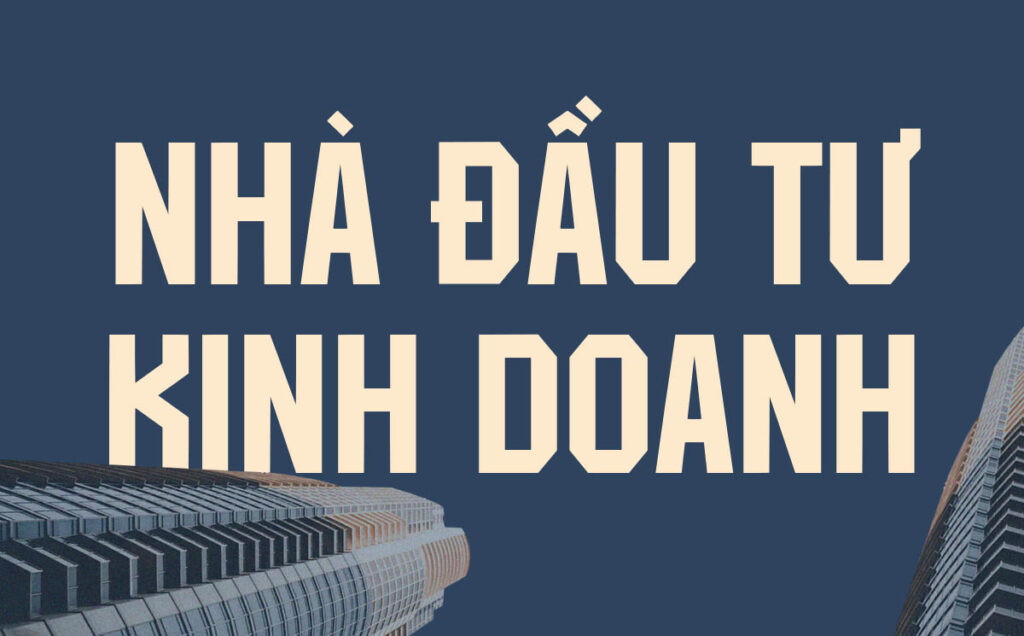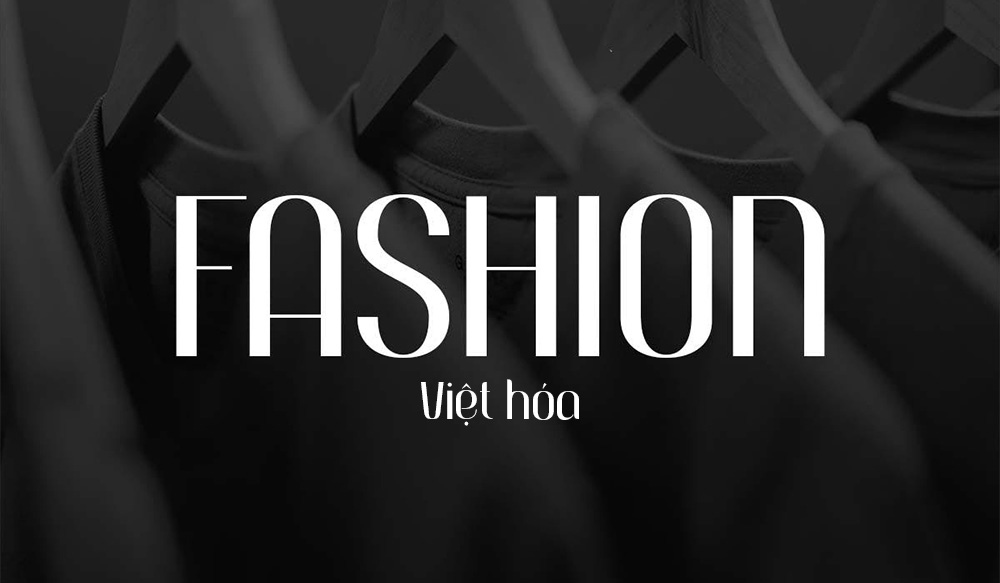
Trong lĩnh vực xây dựng và trình bày hồ sơ kỹ thuật, các bộ font chữ cứng cáp đóng vai trò quan trọng trong việc thể hiện sự vững chãi, uy tín và chuyên nghiệp. Với cấu trúc hình học dứt khoát và trọng lượng nét lớn, dòng phông chữ này thường được ưu tiên cho các tiêu đề dự án, bảng hiệu nhà xưởng hoặc các ghi chú kết cấu trên bản vẽ AutoCAD.
Đặc điểm thẩm mỹ của các dòng font chữ cứng cáp trong thiết kế
Nét lôi cuốn đặc trưng của phông chữ cứng cáp nằm ở sự tuân thủ các quy tắc hình học nghiêm ngặt, với những đường thẳng và góc cạnh sắc sảo. Thiết kế này tạo ra một diện mạo vững chắc như những hệ khung thép trong công trình, giúp thông điệp truyền tải mang tính khẳng định và tin cậy cao. Việc sử dụng font chữ cứng Việt hóa chuẩn Unicode giúp loại bỏ tình trạng lỗi dấu thanh, đảm bảo các ký tự đặc biệt luôn giữ được độ dày nét đồng nhất với thân chữ, duy trì sự mạch lạc cho văn bản.
Sự ổn định của font cứng Việt hóa còn thể hiện ở khả năng hiển thị rõ nét từ khoảng cách xa. Khác với các dòng phông chữ nghệ thuật uốn lượn, phông chữ cứng tập trung vào tính công năng và khả năng nhận diện mặt chữ nhanh chóng. Đây là phương án hiệu quả để định hình phong cách Industrial cho các văn phòng container, nhà lắp ghép hiện đại hoặc những thương hiệu muốn nhấn mạnh vào sự bền bỉ và quy chuẩn kỹ thuật cao.
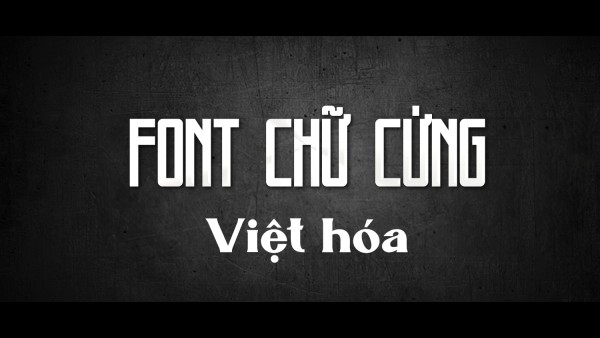
Tư vấn trình bày: Để bản thiết kế đạt được hiệu quả thị giác chuyên nghiệp, bạn nên sử dụng các biến thể đậm (Bold/Black) của font chữ cứng cáp cho các tiêu đề chính. Việc phối hợp cùng một phông chữ không chân mảnh hơn cho phần nội dung thuyết minh sẽ giúp bố cục thông tin trở nên khoa học, tránh cảm giác quá nặng nề cho người đọc.
03 Ứng dụng font cứng Việt hóa vào thực tế công trình
Nhờ diện mạo mạnh mẽ và khả năng hiển thị ổn định, bộ phông chữ này mang lại giá trị thực tế lớn trong khâu quản lý và quảng bá các dự án xây dựng:
- Hệ thống biển hiệu nhà xưởng & Văn phòng: Những nét chữ cứng cáp rất ăn ý khi gia công cắt nổi inox hoặc alu. Kiểu chữ này giúp bảng tên công ty hoặc biển chỉ dẫn nội khu toát lên vẻ chuyên nghiệp, thể hiện quy mô và tính kỷ luật của đơn vị thi công.
- Ghi chú thông số kỹ thuật trên bản vẽ CAD: Độ rõ nét của font chữ cứng cáp hỗ trợ đắc lực cho kỹ sư khi trình bày các thông số vật liệu panel, kết cấu dầm thép, giúp đội ngũ giám sát và thợ thi công tra cứu thông tin chính xác tại hiện trường.
- Thiết kế hồ sơ năng lực và Profile dự án: Sử dụng các biến thể đậm cho tiêu đề chương giúp hồ sơ dự án nhà lắp ghép trông mạch lạc, tạo ấn tượng về một đơn vị có phong cách làm việc ngăn nắp và tư duy kiến trúc hiện đại.
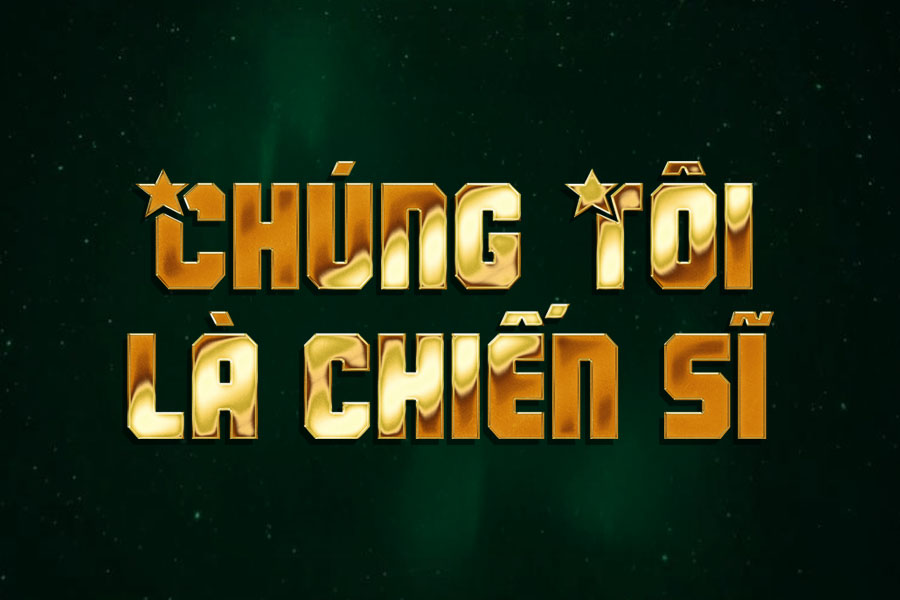
03 Lưu ý kỹ thuật để bố cục phông chữ cứng cáp chuyên nghiệp
Để khai thác hiệu quả vẻ đẹp của dòng font đặc thù này mà không làm rối mắt người xem, người thiết kế nên lưu tâm một số kinh nghiệm sau:
- Kiểm soát khoảng cách chữ: Do phông chữ cứng thường có nét dày và cấu trúc vuông vức, các ký tự có xu hướng trông sát nhau ở kích thước nhỏ. Bạn nên nới rộng khoảng cách giữa các chữ cái một chút để văn bản thông thoáng và dễ đọc hơn.
- Tránh sử dụng cho đoạn văn bản dài: Chỉ nên sử dụng font chữ cứng cáp cho tiêu đề, slogan hoặc các cụm từ nhấn mạnh. Việc lạm dụng cho các đoạn thuyết minh kỹ thuật dài sẽ gây mỏi mắt và làm giảm tính thẩm mỹ của trang giấy.
- Lựa chọn màu sắc có độ tương phản cao: Phông chữ mạnh mẽ phát huy hiệu quả thị giác cao khi phối cùng các tông màu đơn sắc như đen, xám chì hoặc vàng nghệ, giúp các đường nét dứt khoát của bộ chữ được tôn vinh rõ ràng.